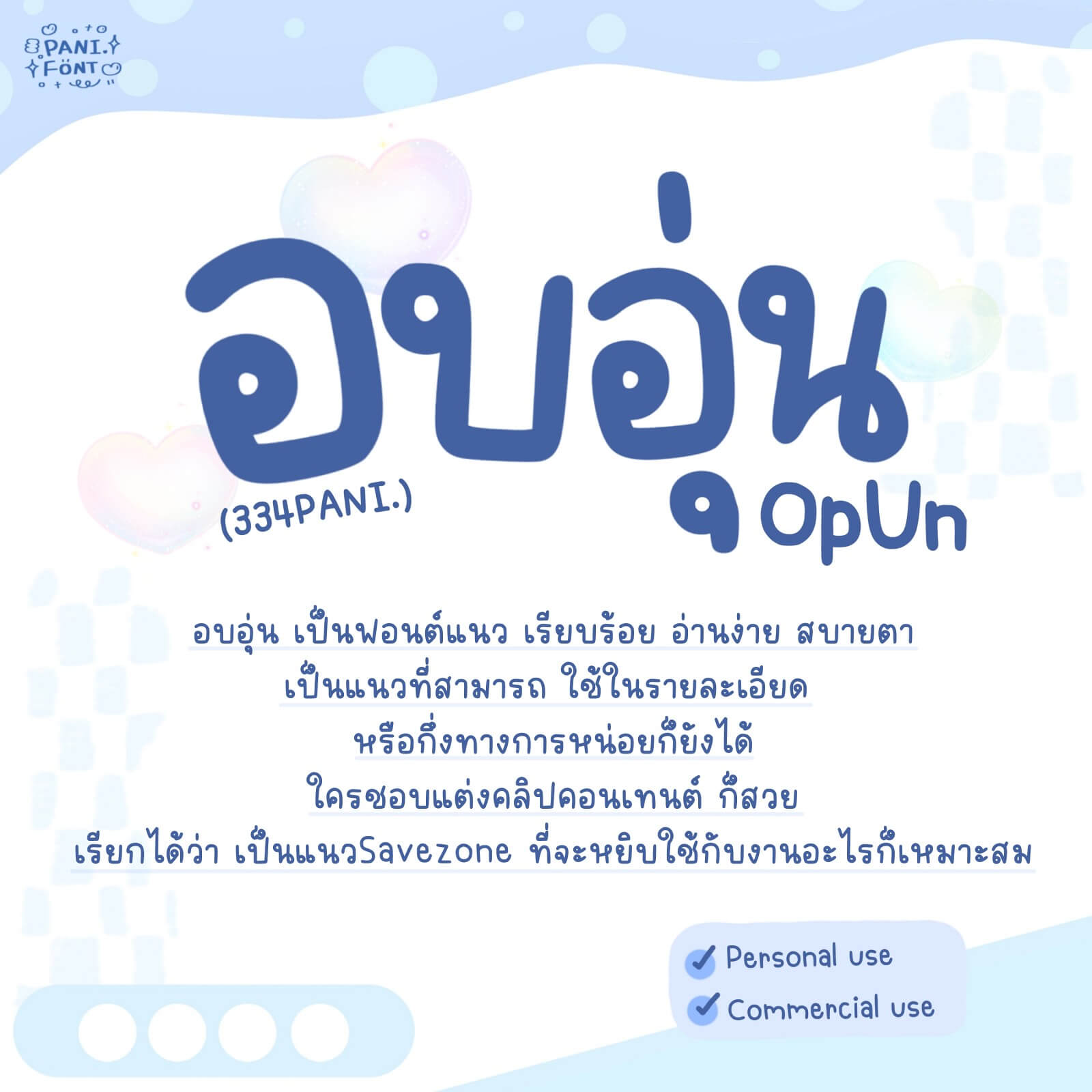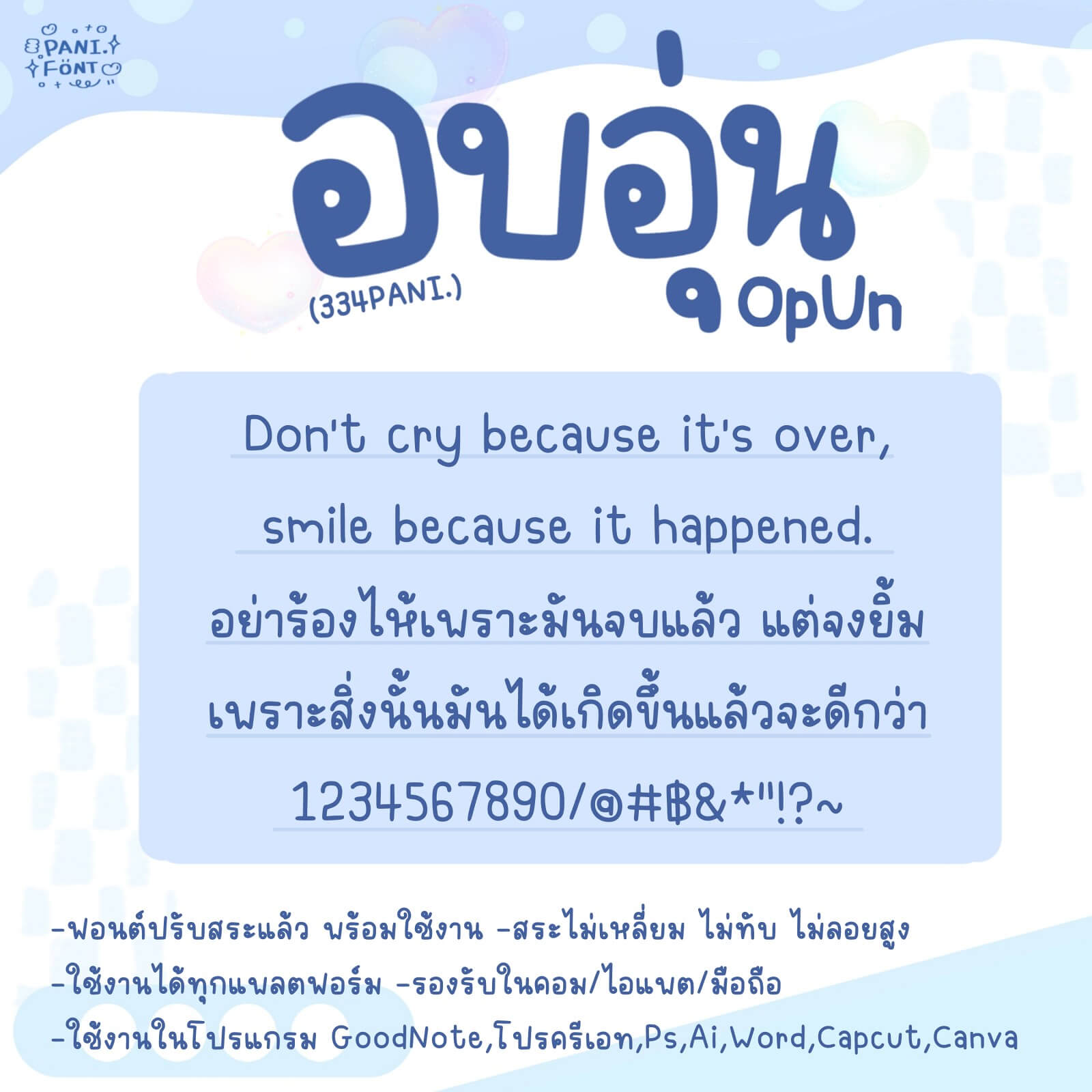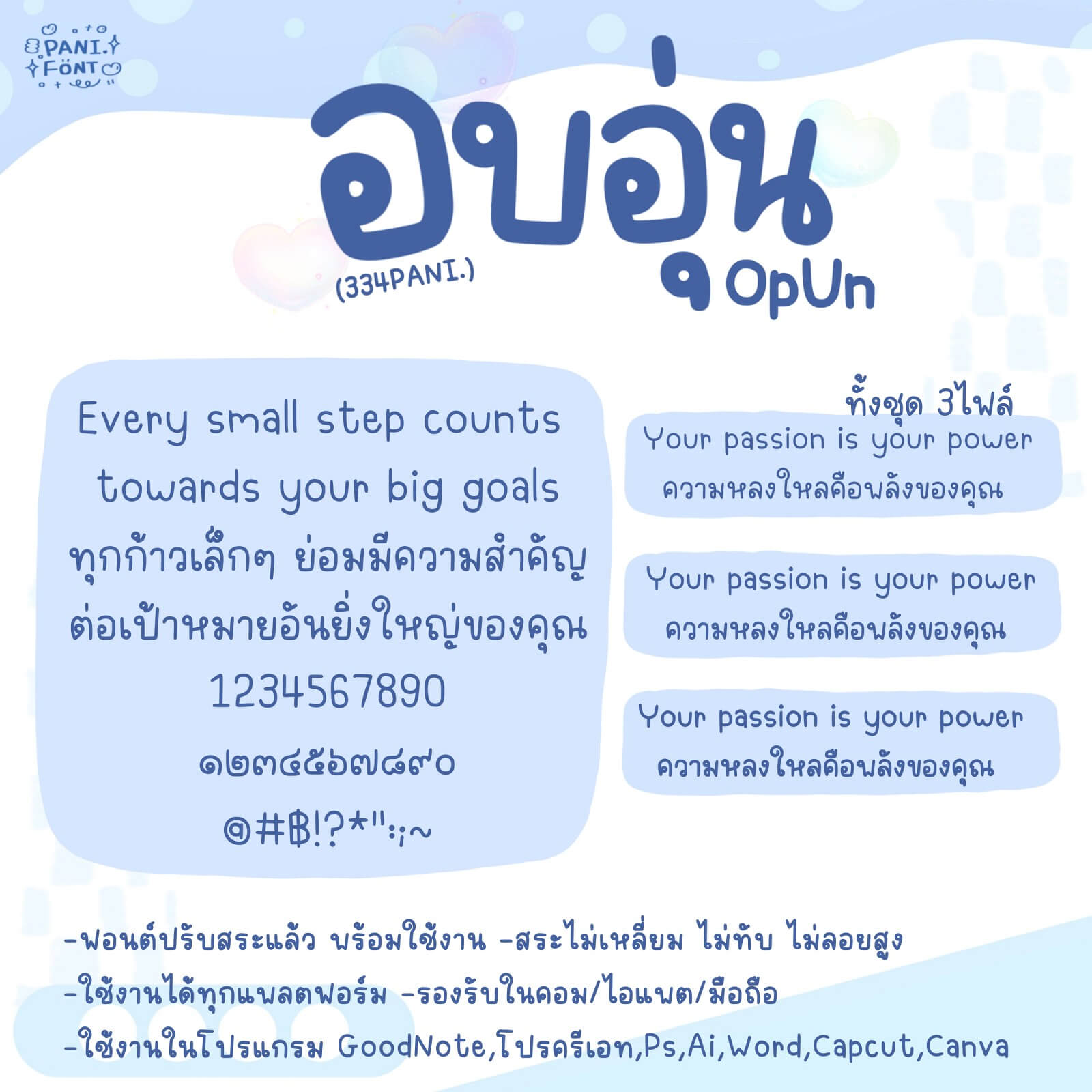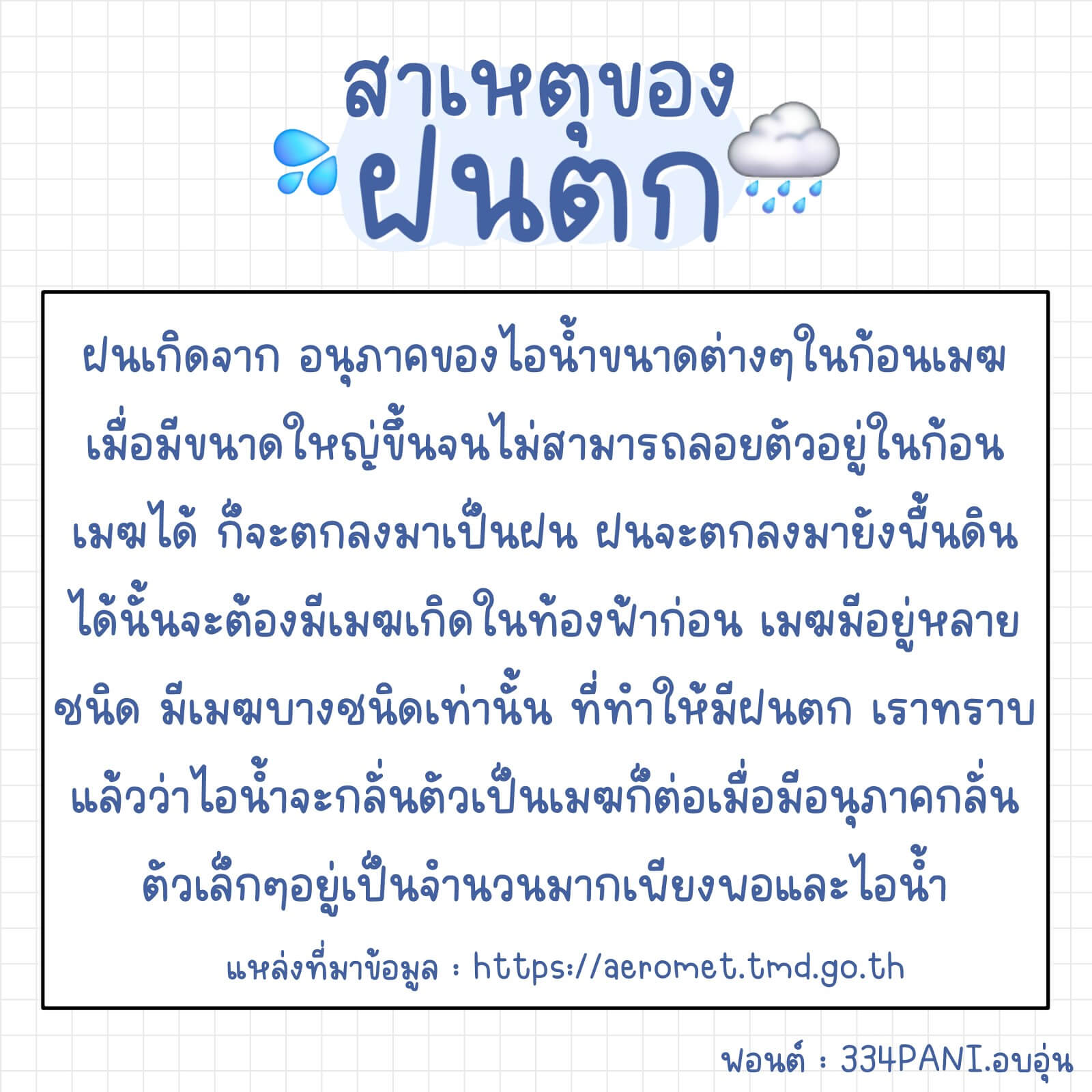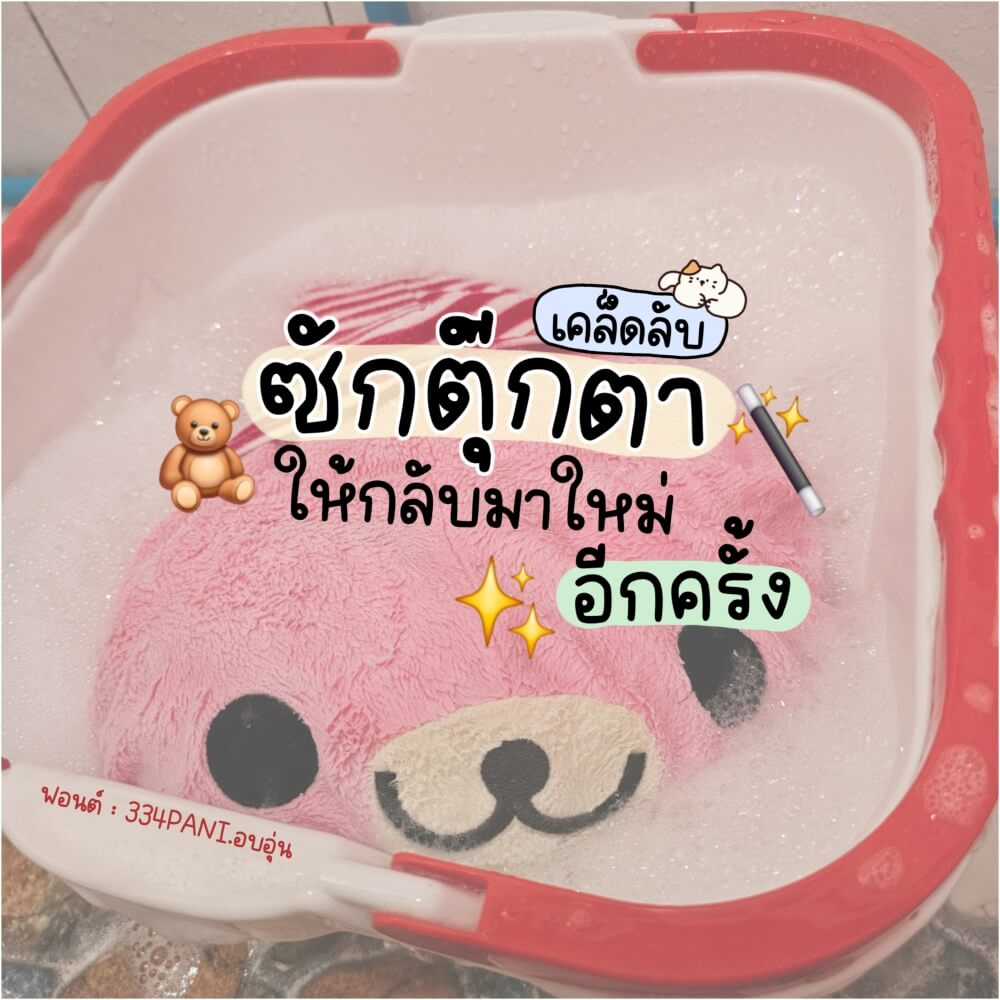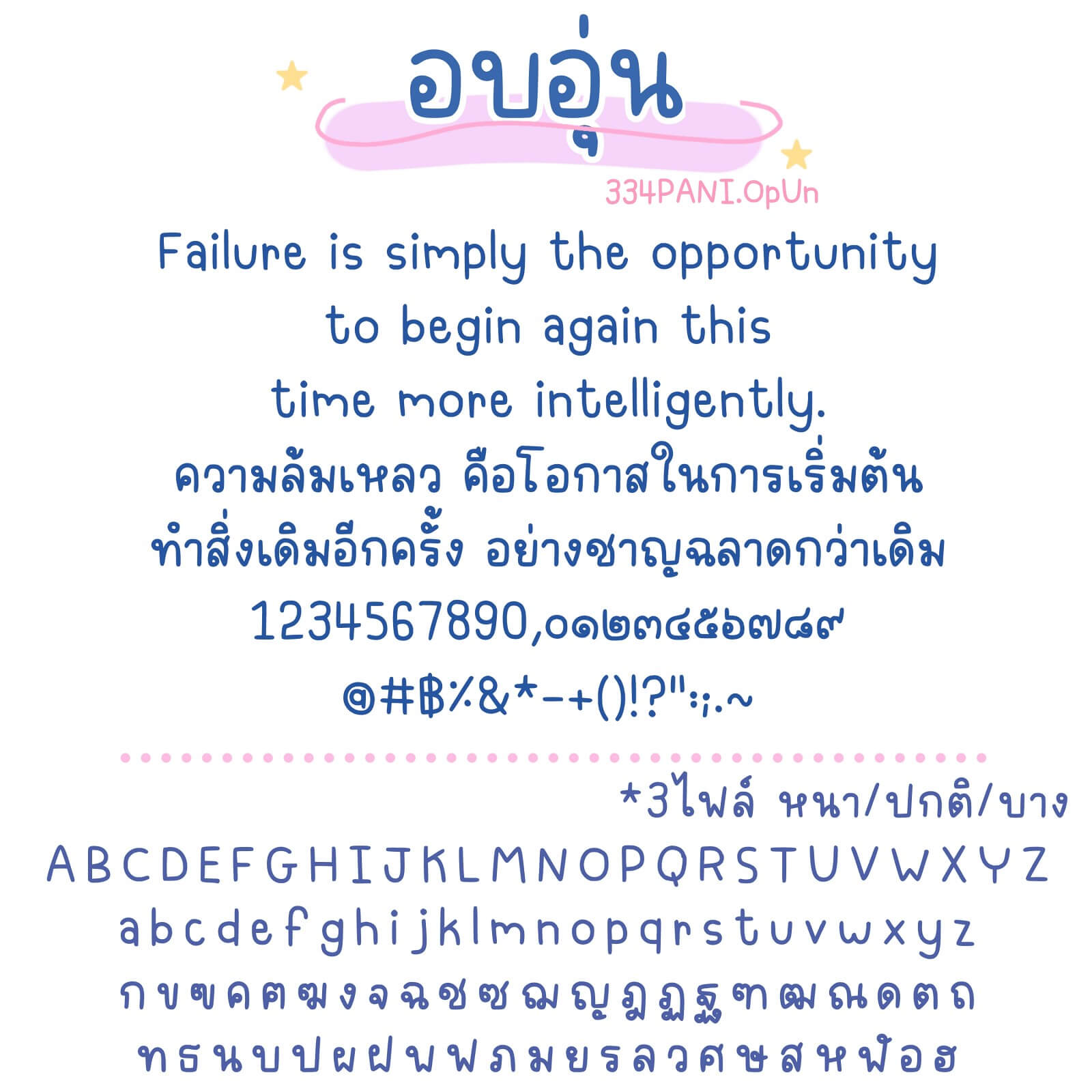
อบอุ่น (334PANIOpUn)
ฟอนต์ 334PANI.อบอุ่น – โหลดทดลองใช้ฟรีตัว Demo อบอุ่น เป็นฟอนต์แนว เรียบร้อย อ่านง่าย สบายตา เป็นแนวที่สามารถใช้ในรายละเอียดหรือกึ่งทางการหน่อยก็ยังได้ ใครชอบแต่งคลิปคอนเทนต์ ก็สวย เรียกได้ว่าเป็นแนว Save zone ที่จะหยิบใช้กับงานอะไรก็เหมาะสม